英字のフリーフォントはたくさんありますが、日本語は文字量の多さ故、あまり種類が豊富ではありません…
と思っていましたが、最近調べてみると日本語のフリーフォントもたくさん増えたように感じています。
なので今回はイマドキで使いやすいおしゃれな日本語のフリーフォントを10種類選びました。
源ノ明朝
東アジアで用いられている4つの言語(簡体中国語、繁体中国語、日本語、および韓国語)に対応しています。
しっぽりアンチック
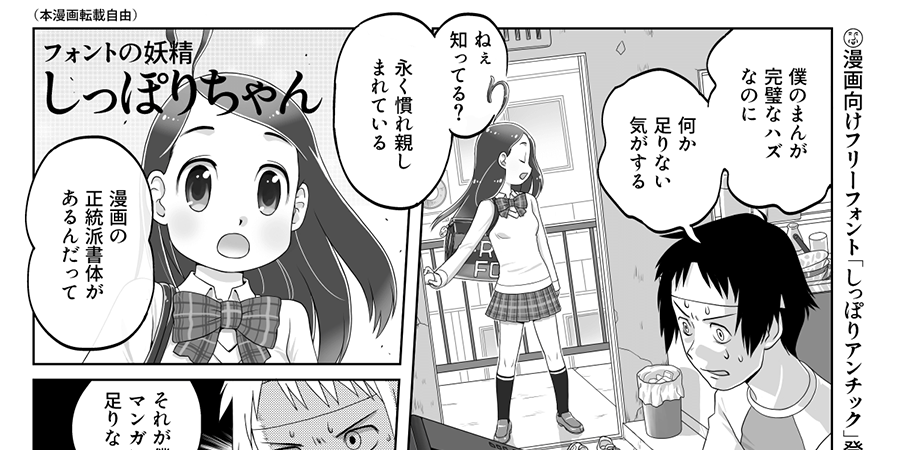
しっぽりアンチック
アンチック体とは、漫画の吹き出しでよく使われている太めの明朝体のようなかな文字で、ゴシック体漢字と組み合わせて使われます。
コミック・漫画の台詞や絵本の文章に適しているフリーフォントです。
アプリ明朝
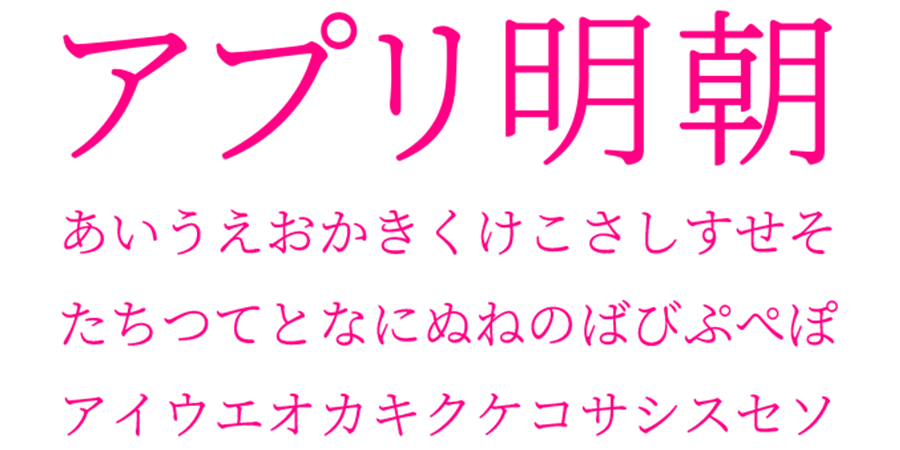
アプリ明朝
アプリ明朝は源ノ明朝の派生フリーフォントです。源ノ明朝より太めで角が丸いのでやわらかい印象です。
ひらがなとの全体の統一感があります。美容系のコンテンツに合いそうです。
はんなり明朝
くるんとした丸文字でふんわりとした印象のフォントです。
築地体を参考にしています。
はれのそら明朝
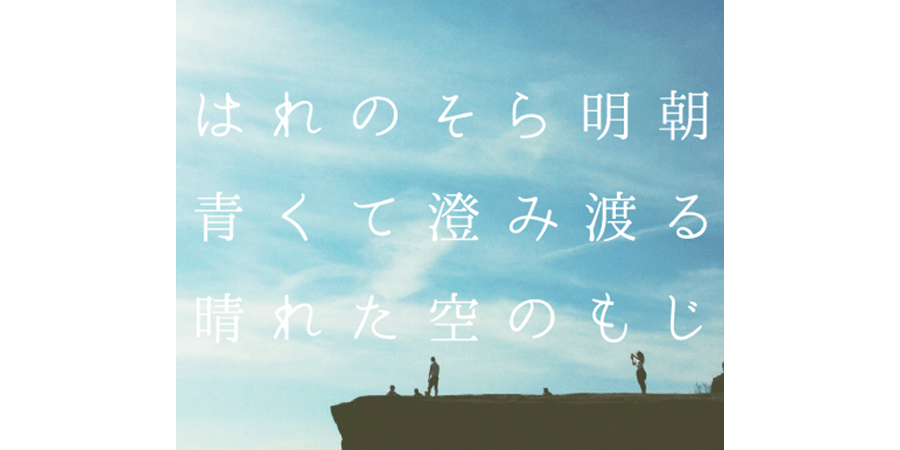
はれのそら明朝
細字ですっきりとした明朝体です。
オールド系のフォントなので懐かしさを感じます。
ぼくたちのゴシック2ボールド
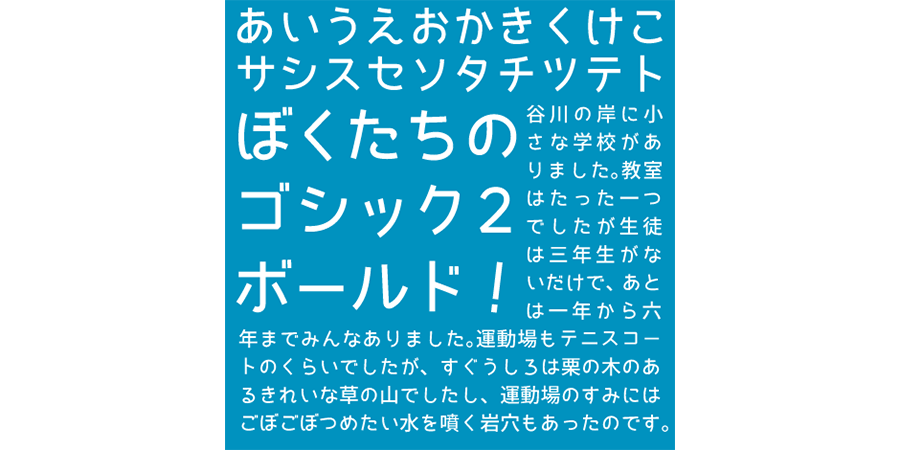
ぼくたちのゴシック2ボールド
曲げの部分が特徴的なゴシック体です。
やんちゃな雰囲気があるので、子供向けのコンテンツに合いそうです。
こども丸ゴシック
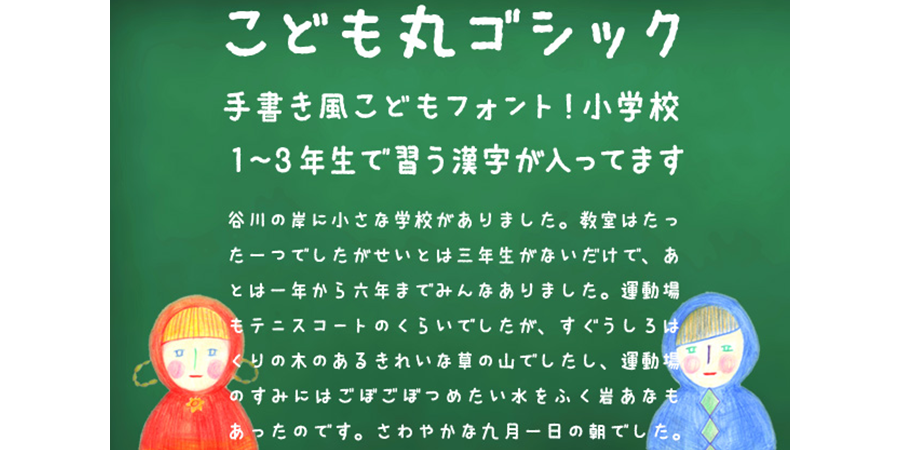
こども丸ゴシック
クレヨンで描いたようなにじみのある太字フォントです。
ぼくたちのゴシックより低年齢向きの印象があります。
せのびゴシック
文字通り背の高いスマートなフォントです。
コンデンスドフォントは個人的に好きなジャンルのフォントです。
オとマのペ
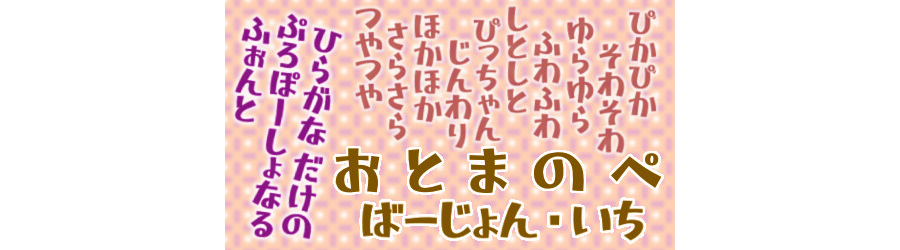
オとマのペ
オノマトペ(擬音語)を表現するにぴったりのフォントです。
マッキーで描いたような楽しそうなイメージです。
TowerGothic KT
クールで安定感のあるどっしりしたフォントです。
キャッチコピーやロゴに合いそうです。